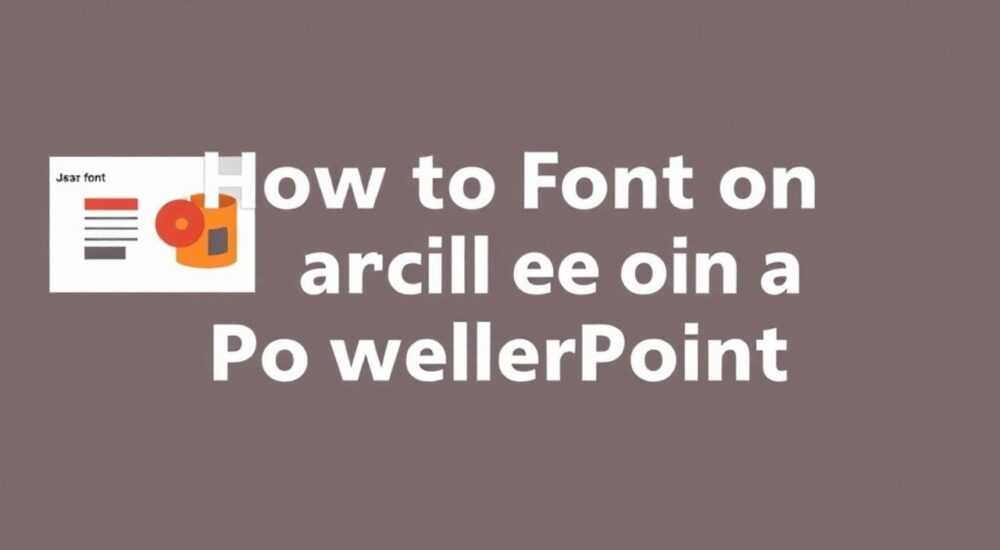
Powerpoint как поменять шрифт на всех слайдах
Изменение шрифта на всех слайдах в PowerPoint — задача, с которой сталкивается почти каждый пользователь при создании презентации. Часто бывает необходимо унифицировать стиль текста, чтобы он соответствовал корпоративному бренду или просто выглядел более профессионально. К счастью, PowerPoint предоставляет инструменты, позволяющие изменить шрифт сразу во всей презентации, не редактируя каждый слайд вручную. Это достигается через работу с образцом слайдов (Slide Master), который определяет базовый стиль для всех слайдов в файле.
Чтобы быстро изменить шрифт на всех слайдах, перейдите в режим «Образец слайдов», выберите основной макет и замените шрифт в заголовках и основном тексте. После сохранения изменений все слайды автоматически обновятся.
Что такое образец слайдов и зачем он нужен
Образец слайдов (Slide Master) — это скрытый уровень в PowerPoint, который управляет общим дизайном всех слайдов в презентации. Он содержит главный слайд и набор вложенных макетов, которые определяют расположение элементов, цвета, эффекты и, что особенно важно, шрифты. Изменяя шрифт в образце, вы автоматически меняете его повсюду, где используется соответствующий стиль текста.
Без использования образца слайдов любое изменение шрифта пришлось бы выполнять вручную на каждом слайде, что крайне неэффективно, особенно в больших презентациях. Образец позволяет централизованно управлять дизайном, обеспечивая единообразие и экономя время.
PowerPoint автоматически применяет изменения из образца ко всем слайдам, основанным на соответствующих макетах. Это означает, что если вы поменяли шрифт заголовка в главном слайде, все слайды с таким заголовком обновятся без дополнительных действий.
Полезно знать: Образец слайдов также контролирует номера страниц, логотипы, фоновые изображения и другие повторяющиеся элементы. Работа с ним — ключ к профессиональному внешнему виду презентации.
Как поменять шрифт на всех слайдах: пошаговая инструкция
Чтобы изменить шрифт на всех слайдах, нужно использовать режим «Образец слайдов». Ниже приведена детальная последовательность действий:
1. Откройте вашу презентацию в PowerPoint.
2. Перейдите на вкладку Вид в верхнем меню.
3. Нажмите кнопку Образец слайдов в группе команд.
4. На экране откроется панель слева с главным слайдом (наиболее крупным) и несколькими макетами под ним.
5. Выберите главный слайд (он обычно первый и самый большой).
6. Найдите текстовые блоки с надписями «Щелчок, чтобы изменить стиль заголовка» и «Щелчок, чтобы изменить стиль текста».
7. Выделите текст внутри каждого блока и измените шрифт через панель инструментов (вкладка «Главная» → группа «Шрифт»).
8. Повторите то же самое для каждого макета, если они используют отличные стили.
9. После завершения нажмите Закрыть режим образца.
10. Проверьте несколько слайдов — изменения должны быть применены.
Если вы хотите изменить только определённый тип текста (например, только заголовки), сосредоточьтесь на соответствующем текстовом поле в образце. При этом обычный текст на слайдах останется без изменений.
«При работе с образцом слайдов всегда начинайте с главного слайда — он задаёт тон всем остальным. Если вы измените шрифт только в одном макете, изменения не распространятся на всю презентацию.» — Анна Петрова, дизайнер презентаций, 8 лет опыта
Что делать, если шрифт не применяется?
Иногда после изменения в образце шрифт на некоторых слайдах остаётся прежним. Это происходит по одной из следующих причин:
• Текст был отформатирован вручную (например, изменён шрифт напрямую на слайде).
• Слайд использует уникальный макет, который не был изменён в образце.
• Применена сторонняя тема с жёстко заданными стилями.
Чтобы исправить ситуацию, можно сбросить форматирование конкретного текстового поля: выделите его и нажмите Очистить всё форматирование на вкладке «Главная». После этого текст снова начнёт подчиняться стилю из образца.
Выбор пар шрифтов: рекомендации и лучшие практики
Правильный выбор шрифтов влияет на восприятие презентации больше, чем может показаться. Хорошая пара шрифтов делает текст читаемым, подчёркивает иерархию и усиливает визуальное воздействие.
Для презентаций чаще всего используют комбинацию из двух шрифтов: один — для заголовков, другой — для основного текста. Заголовочный шрифт может быть более декоративным или жирным, а основной — строго функциональным и удобным для чтения.
Тип презентации
Шрифт заголовка
Шрифт текста
Комментарий
Корпоративная
Calibri Light, Segoe UI
Segoe UI, Arial
Официальный, современный вид
Креативная
Montserrat, Raleway
Open Sans, Lato
Минимализм и стиль
Академическая
Times New Roman
Классика, строгость
Техническая
Arial Bold
Consolas, Courier New
Чёткость и точность
Не стоит использовать более двух шрифтов в одной презентации. Исключение — случаи, когда требуется выделить код, цитаты или специальные блоки.